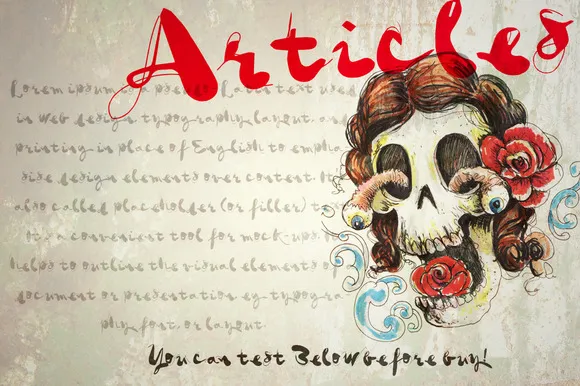
Articles Brush Font – Download Grátis
Introduzimos a fonte brush ‘Articles Brush Font’, uma criação que captura a essência do desenho humano. O texto neste tipo tem as letras subindo e descendo como um dança, cada caractere fluente e dinâmico. Esta fonte apresenta um estilo de escrita clássico chinesa que combina perfeitamente com o moderno design de trabalho. Ideal para dar vida à sua arte digital e adicionar um toque autêntico a qualquer projeto de design, ‘Articles Brush Font’ é uma escolha perfeita para quem busca expressar personalidade em seus projetos visuais. Sempre disponível no formato de fonte, você pode facilmente incorporá-la em suas criações digitais.